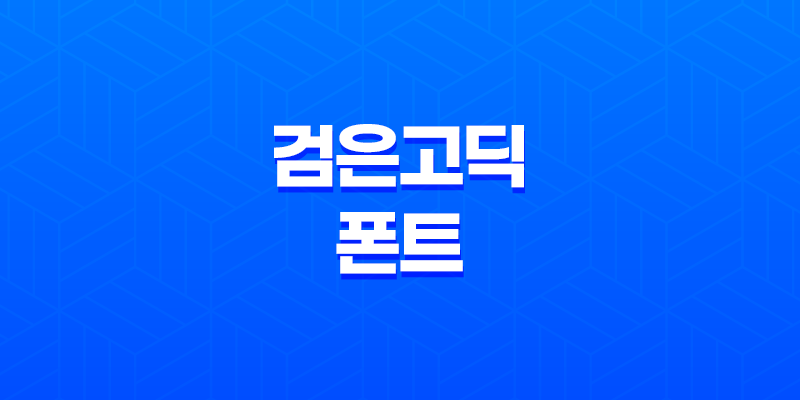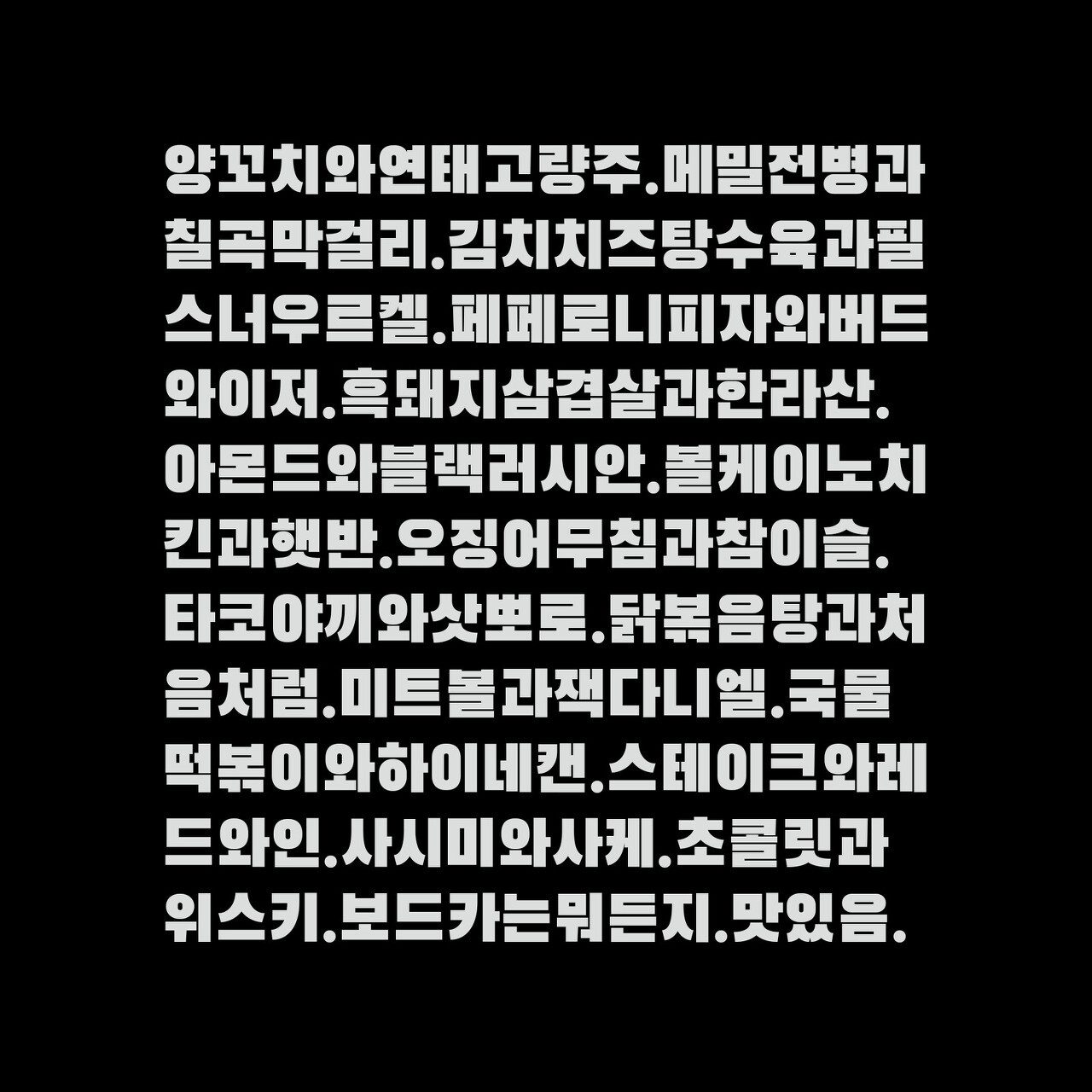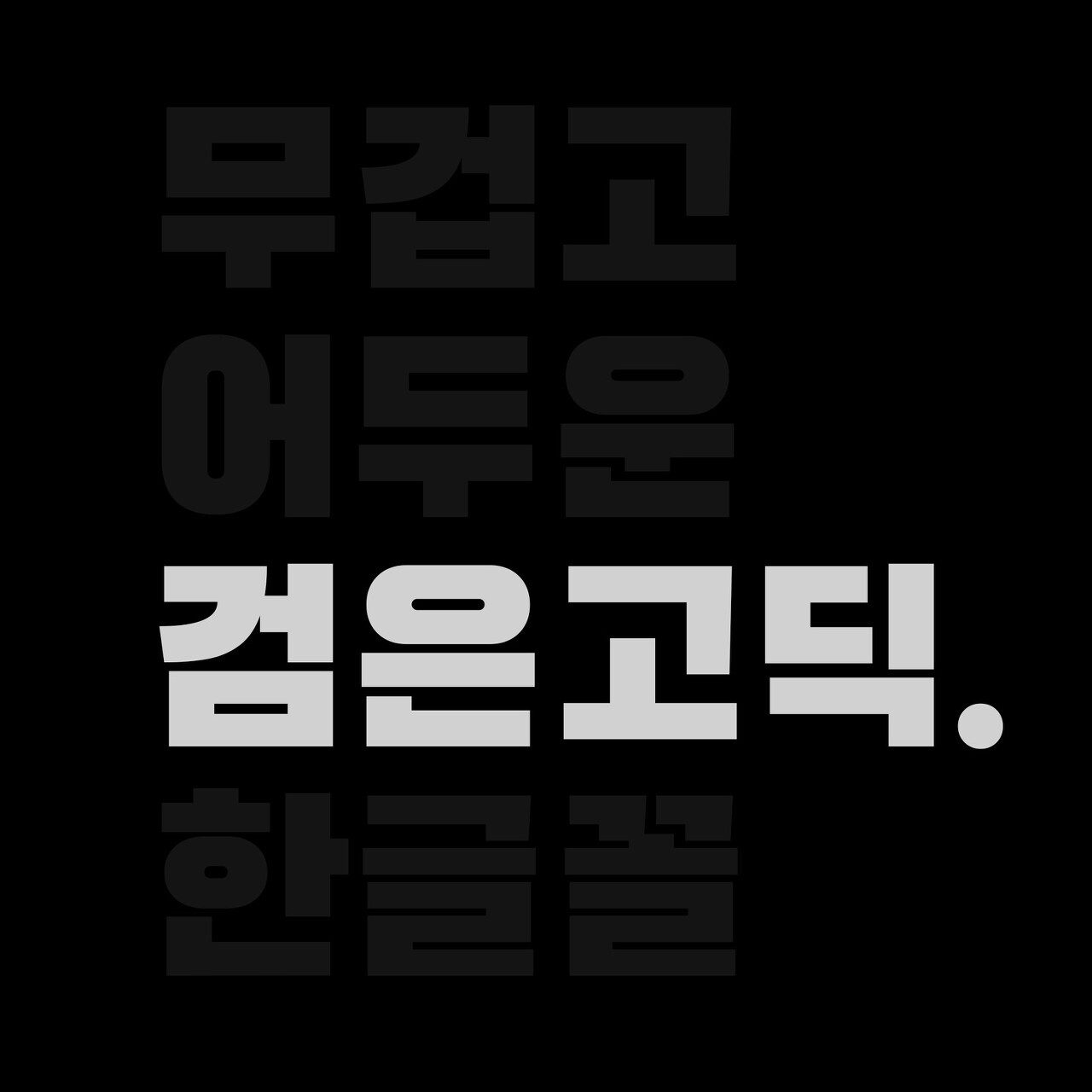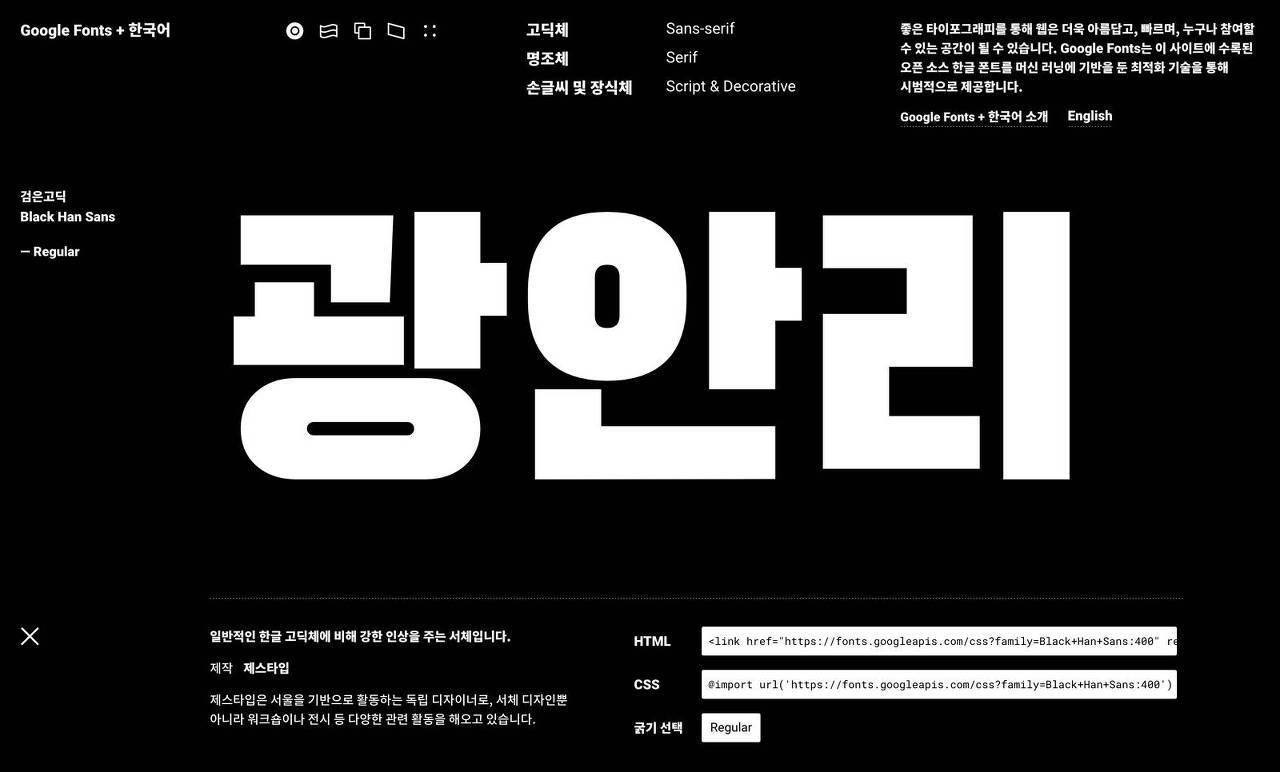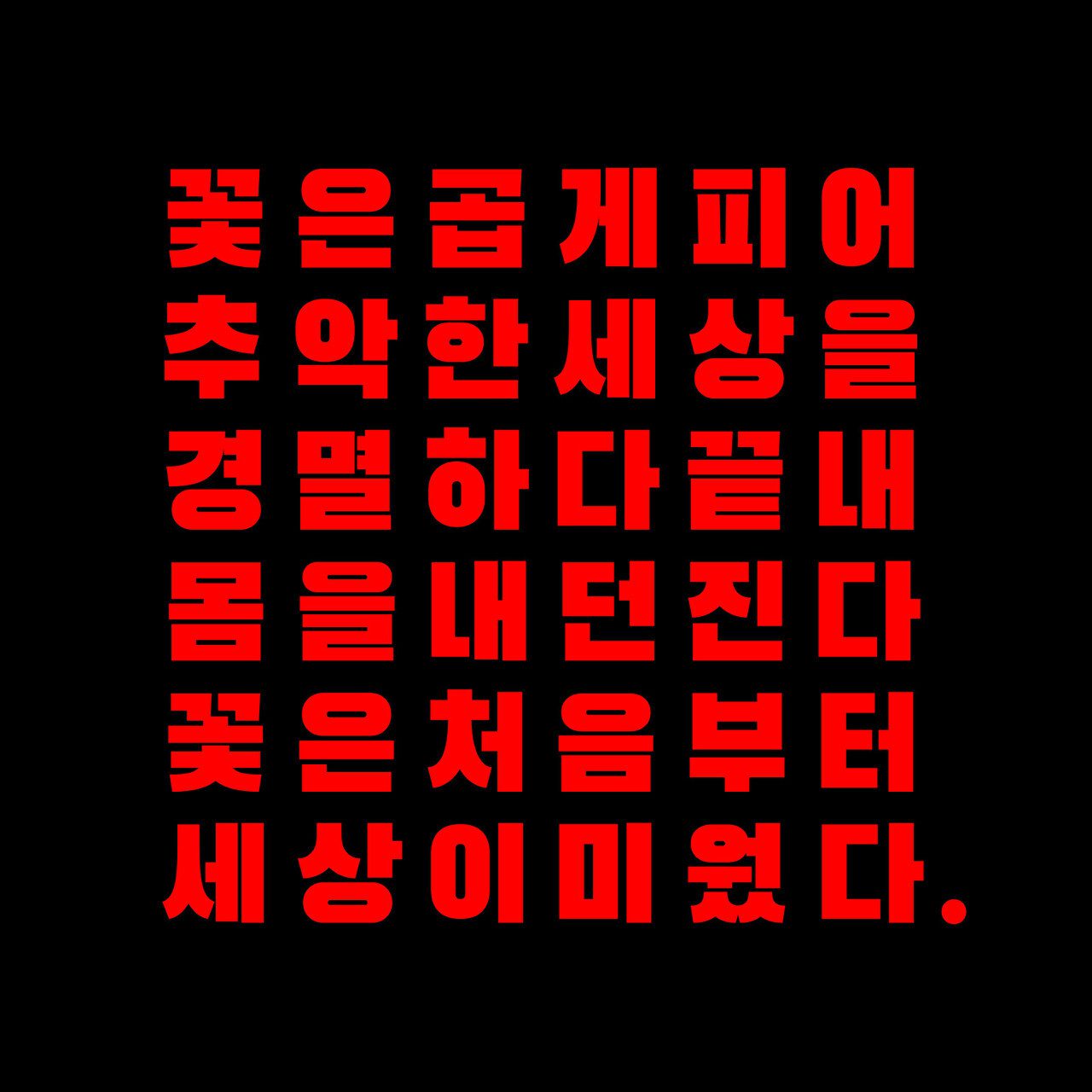
검은고딕 폰트, 타이틀에 어울리는 남성적인 글꼴
가독성과 강렬함을 동시에 잡은 폰트, 검은고딕(Black Han Sans)은 개인이 개발한 것으로, 그 특성상 남성적인 느낌을 주는 글꼴로 꼽힙니다. 무겁고 어두운 디자인의 검은고딕은 특히 ‘타이틀’에 적합한 폰트로 자리매김하고 있습니다.
검은고딕: 웹폰트로 더욱 강력한 활용
검은고딕: 독특한 디자인으로 시선을 사로잡다
시위 현장에서 자주 찾아볼 수 있는 글꼴 중 하나가 검은고딕입니다. 먼 거리에서도 선명하게 보이며 뛰어난 가독성을 자랑합니다. 대기업에서 제공하는 폰트보다 훨씬 우수하며, 실제로 저는 이 폰트를 선호하여 사용하고 있습니다.
검은고딕의 특장점
• 강렬한 시각적 효과
• 뛰어난 가독성
• 웹폰트로 다양한 플랫폼에서 일관된 디자인 유지 가능
나만의 스타일을 찾다, 검은고딕 폰트의 매력
검은고딕 폰트는 남성적이고 무겁게 빛나는 타이틀에 최적화된 선택입니다. 그 독특한 디자인과 웹폰트로의 활용 가능성은 디자이너와 개발자들에게 끊임없는 창의성을 불러일으킬 것입니다.